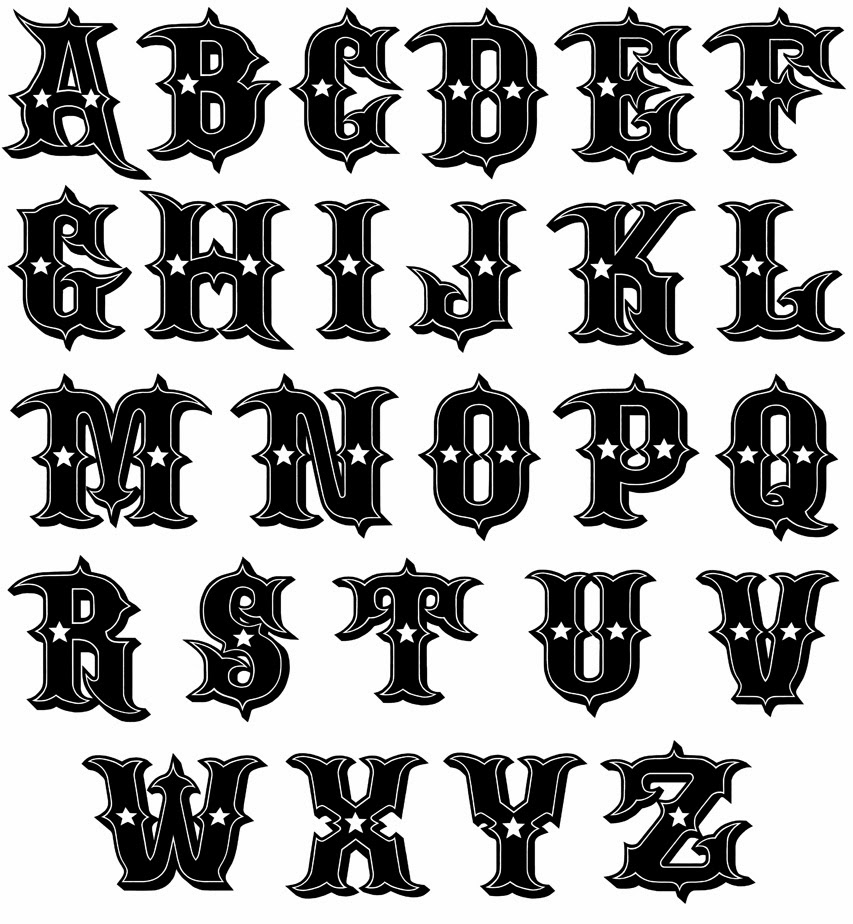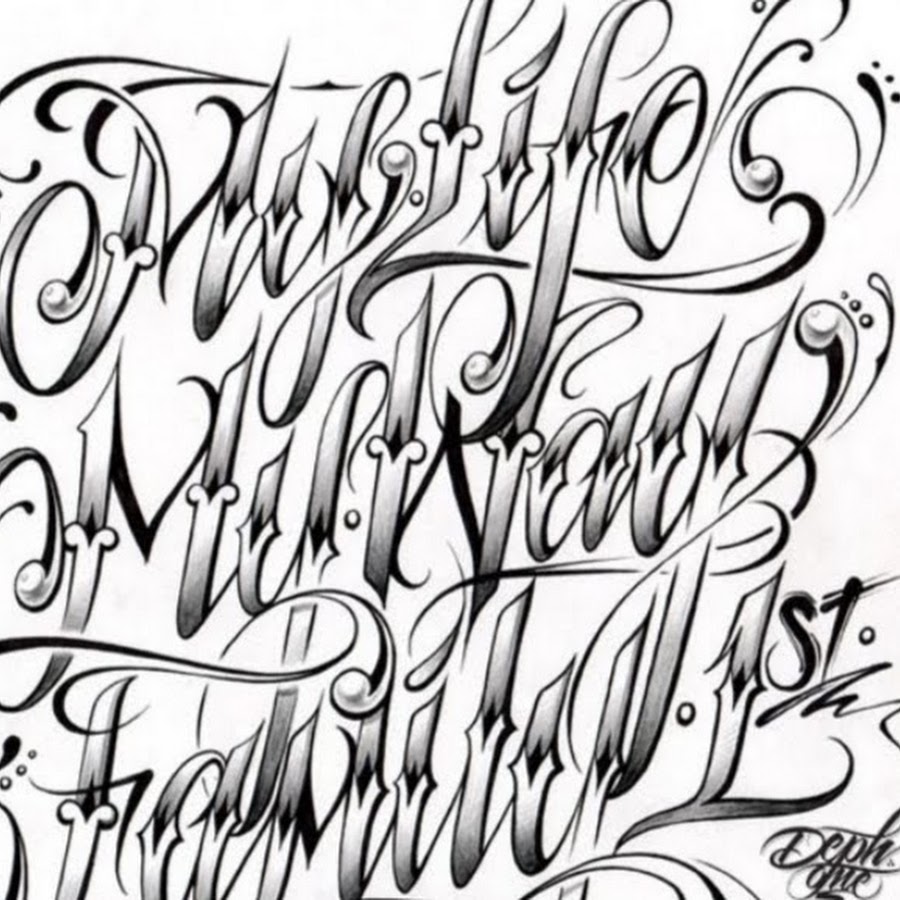
Хотя вы можете создать татуировку практически с любым шрифтом, есть некоторые шрифты, которые сделают ваши татуировки по-настоящему привлекательными. Татуированные шрифты в этом списке варьируются от тех, которые содержат экзотические символы и подробные иллюстрированные глифы, до элегантных рукописных шрифтов. За некоторыми исключениями, все шрифты в этом списке предназначены только для личного использования, что означает, что вы можете использовать их для создания татуировки для себя, но для любых коммерческих целей вам придется связаться с дизайнером шрифтов и приобрести лицензию. Конечно, эти шрифты можно использовать во всех видах графических дизайнерских проектов, не только для татуировок, и кто знает, может, они вдохновят вас на создание собственного шрифта.
Этот красивый шрифт был вдохновлен санскритскими сценариями деванагари и разработан Анандой К.
Махарджан. Он содержит латинские символы, но характерный «overline» придает ему экзотический вид. В отличие от других шрифтов в этом списке, Ananda Namaste бесплатна для коммерческого использования. Вы можете скачать его со страницы разработчика DeviantART в формате TTF.
Blackletter
Blackletter — это жирный шрифт в готическом стиле, который представлен в двух вариантах: стандартный и контурный. Он также доступен для коммерческого использования и может быть загружен в формате TTF. Blackletter, разработанный Дитером Штеффманом, является отличным шрифтом для всех, кто хочет сделать несколько традиционную, но визуально захватывающую татуировку.
племенной
Племенные татуировки всегда популярны, так что вы не ошибетесь с этим шрифтом татуировки. Tribal — это четкий шрифт, также доступный для коммерческого использования. Это приходит в двух стилях; оба являются файлами TTF. Ваша татуировка будет разборчивой и достаточно интересной, чтобы привлечь внимание.
Bombora
Bombora использует стиль, похожий на племенной дизайн, но с более толстыми мазками, которые напоминают кисть. Это шрифт OTF, который одинаково хорошо будет смотреться на татуировках, в заголовках или на постерах.
Nurkholis
Nurkholis — это фантастический шрифт, который берет строчные буквы латинского алфавита и творчески комбинирует их, чтобы ваше письмо выглядело как арабский шрифт. Если вы поклонник арабской каллиграфии, этот шрифт идеально подойдет вам, хотите ли вы использовать его для татуировки или других проектов. Нурхолис — это шрифт TTF.
Delinquente
Delinquente — это профессионально выглядящий шрифт со множеством штрихов. Это здорово, если вы хотите сделать свою татуировку заметной и читаемой. Он доступен как TTF, но только демо-версия бесплатна (в ней отсутствуют некоторые специальные символы).
Тату Тяжелый
Tattoo Heavy использует толстые, нетрадиционные штрихи, которые приводят к действительно привлекательным символам.
Он доступен в формате TTF и подходит для коротких татуировок, а также для постеров, логотипов и заголовков. Однако для коммерческого использования вам придется связаться с создателем.
Mardian
Mardian — это классический, сложный скрипт-шрифт с орнаментальными инициалами, поэтому его вполне можно использовать и как монограммный шрифт. Демо-версия поддерживает некоторые расширенные символы и поставляется в формате TTF. Для коммерческого использования вам необходимо приобрести полный шрифт.Скачать
Тату
Вы можете подумать «что, еще один шрифт с« племенным »в названии?», Но этот полностью отличается от предыдущего шрифта с племенной татуировкой. Как вы можете видеть, это шрифт дингбат, что означает, что он использует специальные символы и фигуры вместо цифр и букв. Эти символы являются популярными мотивами татуировки, и этот шрифт облегчает вам создание дизайна татуировки — просто выберите символ, распечатайте его и принесите в свой магазин татуировок.
Tribal Tattoo — это шрифт TTF, и он бесплатный для личного использования.
Angilla
Angilla — действительно привлекательный шрифт с толстыми штрихами, напоминающими каллиграфические шрифты. Я вижу, что это используется для заголовков и постеров, а также татуировок. Вы можете скачать его в формате TTF.
Средневековый писец
Medieval Scribish — это шрифт с татуировкой, выполненной из цельных кепок, с художественным и немного средневековым оттенком. Хорошие новости — это бесплатно для коммерческого использования! Загрузите файл TTF и начните работать над своим удивительным дизайном татуировки.Скачать
Unzialish
Unzialish выглядит стильно, немного экзотично, немного эльфийски и на 100% подходит для вашей новой татуировки. Этот шрифт TTF также бесплатен для коммерческого использования и поддерживает некоторые расширенные символы.Скачать
Тенгвар Аннатар
Говоря об эльфийском … Tengwar Annatar — это шрифт, полностью вдохновленный эльфийским языком из работ Дж.
Р.Р. Толкина. Таким образом, это идеальный шрифт для всех любителей фэнтези и поклонников Толкина, которые планируют сделать татуировку. Он также бесплатный для коммерческого использования и доступен в виде шрифта TTF в четырех стилях.Скачать
Tattoo fonts can be used to preview and decide your text-based tattoos. Pure text tattoos become more and more trendy these days since more and more people choose words, names, short quotes and meaningful sayings to express themselves through their tattoos.